Das »Trajanische Alphabet« ist eine antike Inschrift (Epigraph) am Sockel der Trajanssäule (Columna Traiana) in Rom. Sie gilt als das berühmteste Beispiel für die Capitalis Monumentalis und formvollendete Vorlage für alle runden Schriften römischen Ursprungs bzw. Antiqua-Schriften.
Die Variante der Capitalis Monumentalis an der Columna Traiana in Rom gilt unter Schriftgelehrten als das schönste Beispiel römischer Schriftkunst. Der Begriff Trajanisches Alphabet etablierte sich, weil dieses Majuskelalphabet (Großbuchstabenalphabet), mit Ausnahme von H, J, K, U, W, Y und Z, in Form einer Inschrift auf einer 115 cm hohen und 275 cm breiten Marmortafel eingemeißelt (Lapidarschrift) wurde, die sich auf dem würfelförmigen Sockel der Trajanssäule befindet.
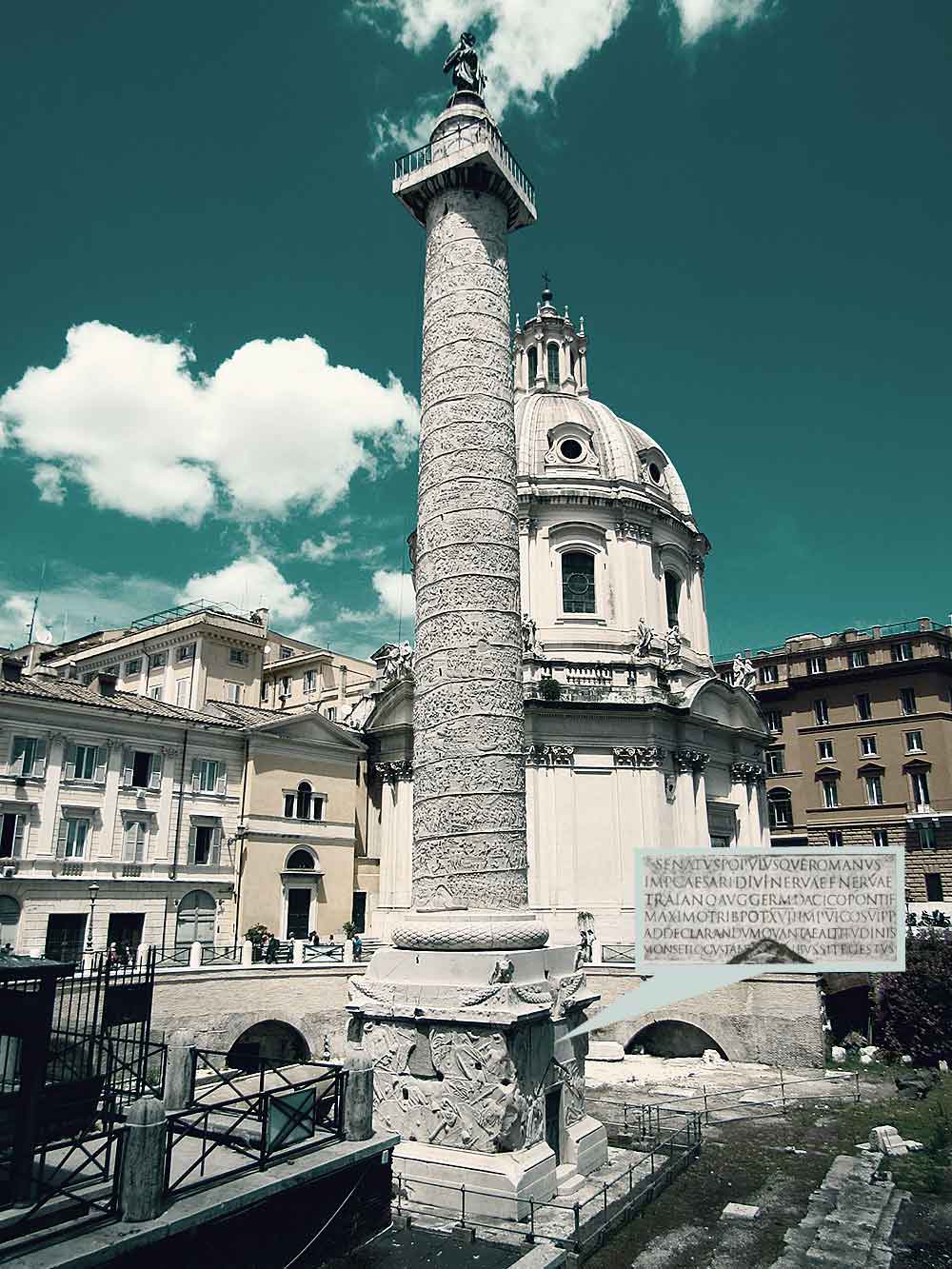
Die Trajanssäule wurde von »Apollodoros aus Damaskus« (Römischer Baumeister und Ingenieur aus Syrien, um 65–130) nach den persönlichen Anweisungen des römischen Kaisers Marcus Ulpius Traianus (53–117) und unter der Mitarbeit erfahrener Bildhauer und Künstler auf dem Trajansforum 1) in Rom zwischen den beiden – später von römischen Kaiser Konstantin I. (Flavius Valerius Constantinus, um 270/288–337) zerstörten – kaiserlichen Bibliotheken und der Basilika Ulpia errichtet. In der kunstgeschichtlichen Literatur wird die Vollendung und Weihe der Säule auf den 18. Mai 113 datiert.
Die Trajanssäule erinnert u.a. an die Entstehungsgeschichte der Trajansmärkte, an deren Stelle extra ein Berg abgetragen werden musste. Die Stele selbst schmückt eine spiralförmige Reliefdarstellung mit einer Länge von rund 200 Metern, welche zwei Feldzüge Trajans gegen die Daker darstellt. Seit 1588 krönt die Säule anstatt der Kaiserstatue eine Petrusstatue.
Die Inschrift des Sockels ist in lateinischer Sprache verfasst und besteht aus sechs Zeilen im Zweiliniensystem, deren Majuskelhöhe (Versalhöhe) sich von 11,5 cm (ersten zwei Zeilen) auf etwa 9,75 cm (letzte Zeile) verringert. Die Zeilenabstände verringern sich von 7,5 cm auf 7 cm. Die Worte, Römischen Zahlen und Abkürzungen sind durch dreieckige Satzzeichen ohne Wortzwischenräume voneinander getrennt, welche auf der Mittelhöhe der Majuskeln eingemeißelt wurden.
Die Inschrift lautet …
SENATVS·POPVLVSQVE·ROMANVS IMP·CAESARI·DIVI·NERVAE·F·NERVAE TRAIANO·AUG·GERM·DACICO·PONTIF MAXIMO·TRIB·POT·XVII·IMP·VI·COS·VI·P·P ADDECLARANDVM·QVANTAE·ALTITVDINIS MONSET·LOCUS·TANTIS·RVDERIBUS·SIT·EGESTVS
Deutsche Übersetzung nach Walter Ohlsen 2) …
Der Senat und das Volk von Rom dem Gebieter, Kaiser, des göttlichen Nerva Sohn Nerva Trajanus Augustus, Germanicus, Dacier, oberster römischer Priester, 17 Mal Tribun, 6 Mal Feldherr, 6 Mal Konsul, Vertreter des Vaterlandes, um zu zeigen, von welcher Höhe der Berg und die Steine waren, die für derartig Werke genommen wurden.
Schriftsachverständige gehen davon aus, dass sowohl der Sockel, die Säule als auch die Majuskeln nach dem Reihenfolgenprinzip des Archimedes »Kegel, Kugel, Zylinder« im Verhältnis 1:2:3 (Zylinder vom Radius r und der Höhe 2 r, einer Kugel vom Radius r und eines geraden Kegels vom Radius r und der Höhe 2 r) konstruiert wurden. Auf das Zweidimensionale bezogen entspricht das Quadrat, Kreis und Dreieck, den Grundformen unseres westeuropäischen Alphabets.
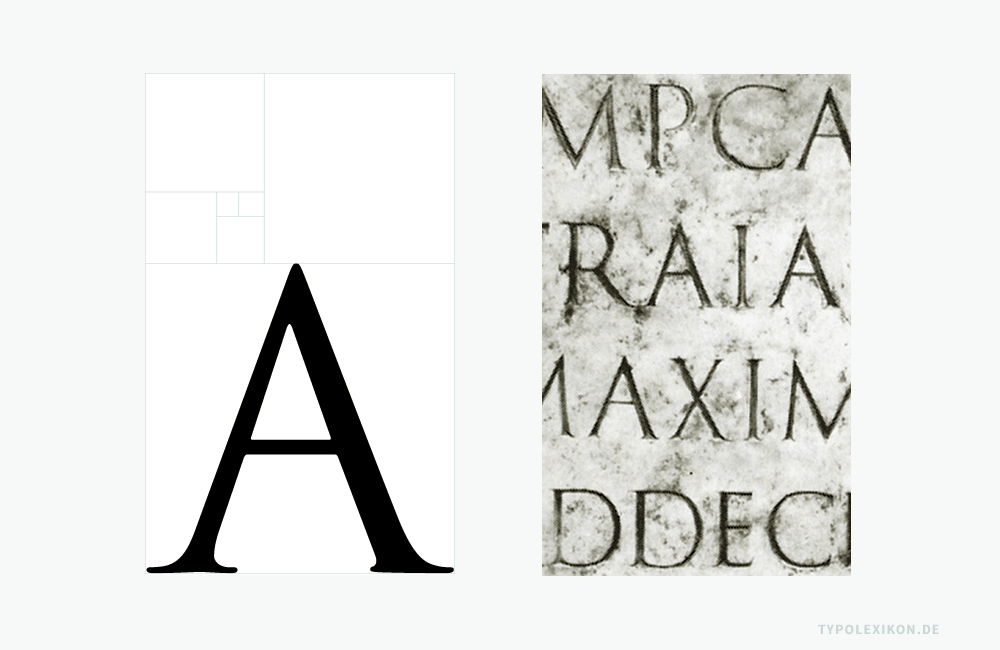
Das Trajanische Alphabet inspirierte Generationen von Schriftgelehrten und Typografen, insbesondere seit der italienischen Renaissance. So u.a. Vespasiano Amphiareo (Kalligraph und Buchgestalter, um 1490–1563), Wolfgang Fugger (Schreibmeister, um 1515–1568) , Geoffroy Tory (Buchdrucker des französischen Königs und Mentor von Claude Garamond, 1480–1533), Albrecht Dürer (Maler, Grafiker, Mathematiker und Kunsttheoretiker, 1471–1528), Francesco Torniello (Typograf und Schriftsteller, um 1490–1589), Luca Pacioli (Kalligraph und Mathematiker, um 1445/1514 oder 1517), Damiano da Moile (Buchbinder, Kalligraph und Typograf, um 1450–1500/1510), Leonardo da Vinci (Künstler und Universalgelehrter, 1452–1519) , Felice Feliciano (Kalligraph und Schriftgelehrter, um 1433–1479), Claude Garamond (Schriftschneider, um 1498/99–1561), Jan Tschichold (Grafikdesigner und Typograf, 1902–1974) und Günter Gerhard Lange (Schriftgestalter und Typograf, 1921–2008). 3)
Bis heute konnte allerdings nicht nachgewiesen werden, ob das Trajanische Alphabet mittels der Typometrie konstruiert wurde, oder ob es mittels eines »eingeübten Auges« entstand.